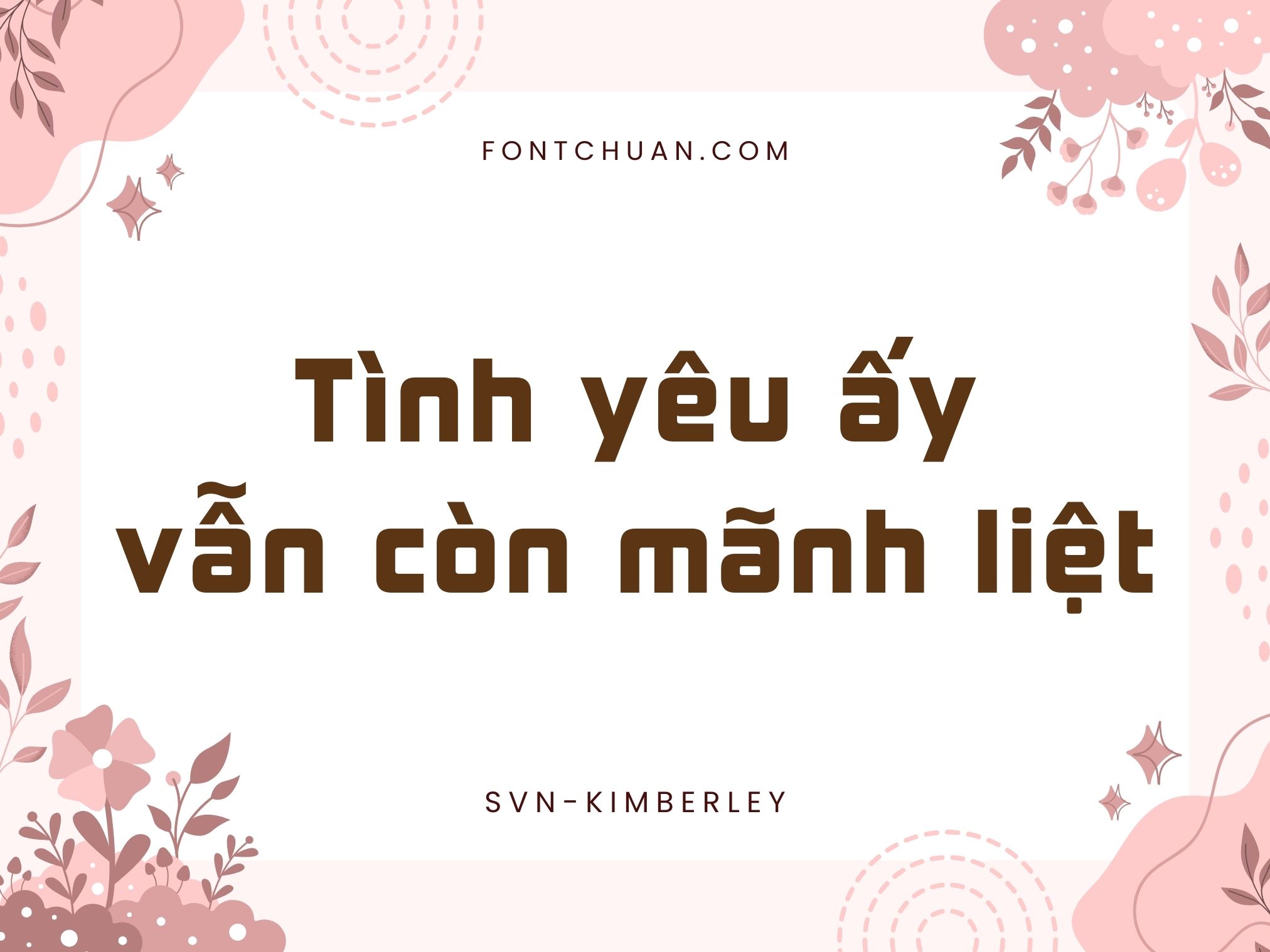
Font SVN Kimberley Việt Hóa
Font SVN Kimberley là phiên bản Việt hóa của kiểu chữ Kimberley, được thực hiện bởi STYLEno.1 Fonts. Kimberley là một kiểu chữ sans-serif lấy cảm hứng từ các logo công nghiệp và doanh nghiệp của thập niên 1970, với thiết kế vuông vức kết hợp cùng các góc cạnh sắc nét, tạo nên vẻ ngoài mạnh mẽ và hiện đại. Font này bao gồm đầy đủ các ký tự chữ hoa, chữ thường, chữ số và dấu câu, hỗ trợ đa ngôn ngữ. Ngoài ra, Kimberley còn cung cấp các ký tự thay thế stylistic cho số 4 và chữ W, giúp tăng tính linh hoạt trong thiết kế. Font này phù hợp cho nhiều mục đích sử dụng như thiết kế logo, tiêu đề, bao bì sản phẩm và các ấn phẩm truyền thông.
SVN Kimberley lý tưởng cho các dự án thiết kế yêu cầu sự mạnh mẽ và hiện đại, như thiết kế logo thương hiệu, tiêu đề tạp chí, bao bì sản phẩm và các ấn phẩm truyền thông. Các ngành nghề như quảng cáo, giáo dục và công nghệ có thể tận dụng font này để tạo điểm nhấn trong thiết kế. Ngoài ra, font cũng thích hợp cho các sự kiện như Tết, Giáng sinh, Valentine và các lễ hội khác.